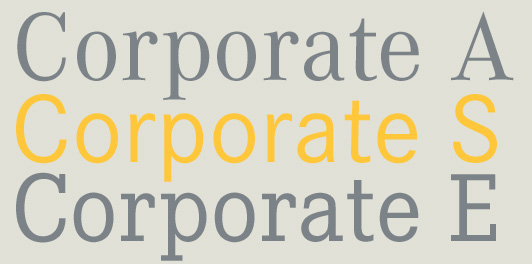
Trilogia ASE, de Kurt WeidemannO mais conhecido clãs de fontes é a Corporate ASE, conjunto de caracteres que o tipógrafo alemão Kurt Weidemann desenhou para Corporate Typography da Mercedes-Benz (hoje Daimler Chrysler).A Corporate ASE foi adoptada por esta multinacional a partir de 1989. Kurt Weidemann desenhou a seguinte trilogia: versão A (Antiqua), serifada versão S (Seriflose), sem serifa versão E (Egyptienne), serifa-grossa Todas as três versões têm o mesmo esqueleto, a mesma estrutura interna, os mesmos pesos e as mesmas itálicas, pelo que harmonizam perfeitamente entre si até são intercambiáveis, sempre que seja necessário fazer substituições.
O Livro de Normas da Corporate Identity da Mercedes- Benz define claramente os campos de utilização para cada grupo: A versão serifada A é para uso geral em todos os displays, anúncios publicitários, revistas de marketing (veja um exemplar na coluna ao lado) e todos os demais campos de representação da marca com a estrela de três pontas. A versão sem serifas S foi reservada para temas informativos, sem tendência representativa. Dentro da trilogia ASE, esta sem serifa é a que menos impacto visual tem; contudo, contrasta bem com a versão A.
A versão E está reservada para toda a documentação técnica, manuais, brochuras. Esta serifa- grossa inspirou-se na Clarendon. A ASE (1989/90) poderá ser um dos exemplos mais conhecidos, mas existem mais clãs de fontes por exemplo